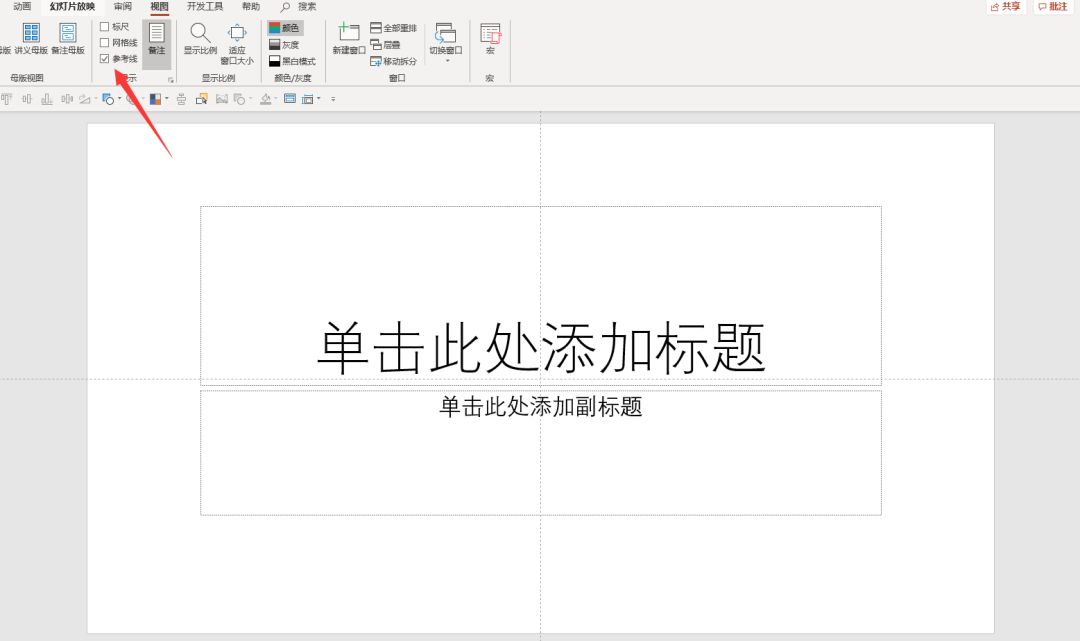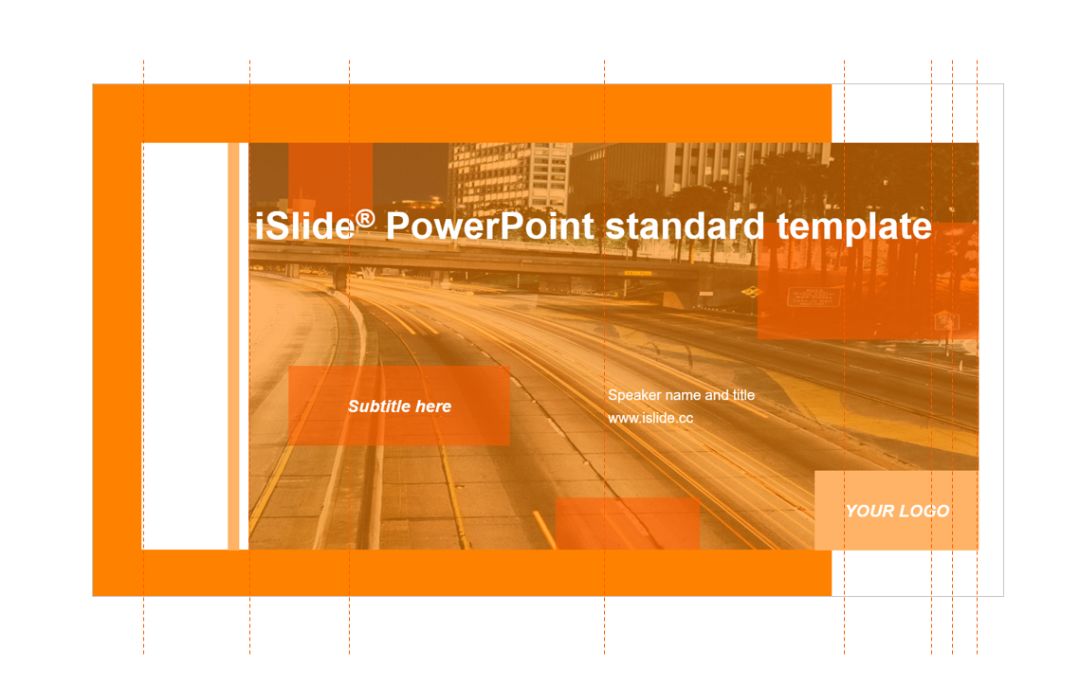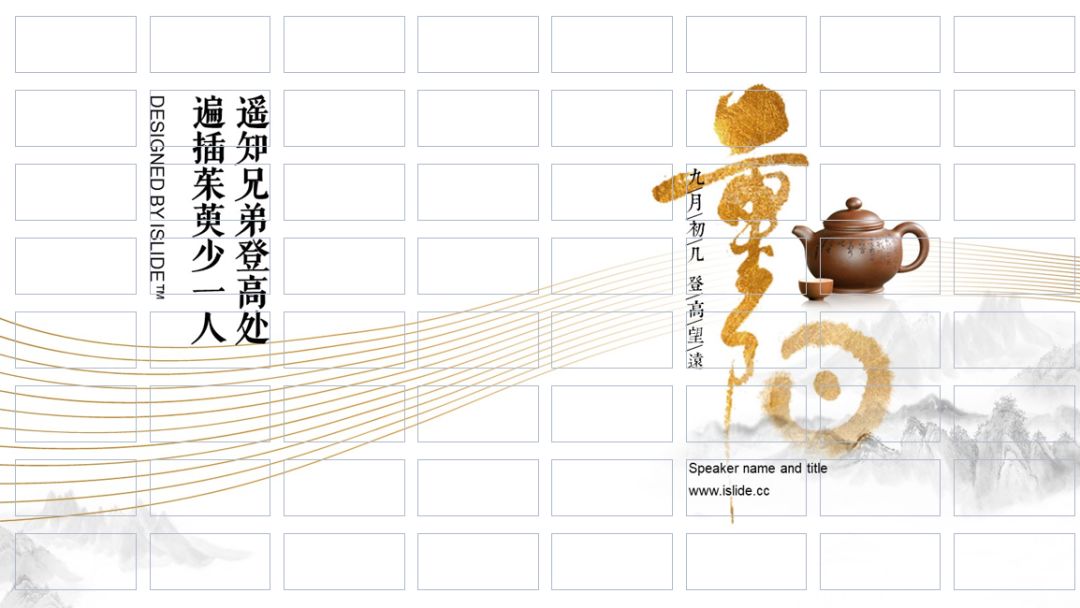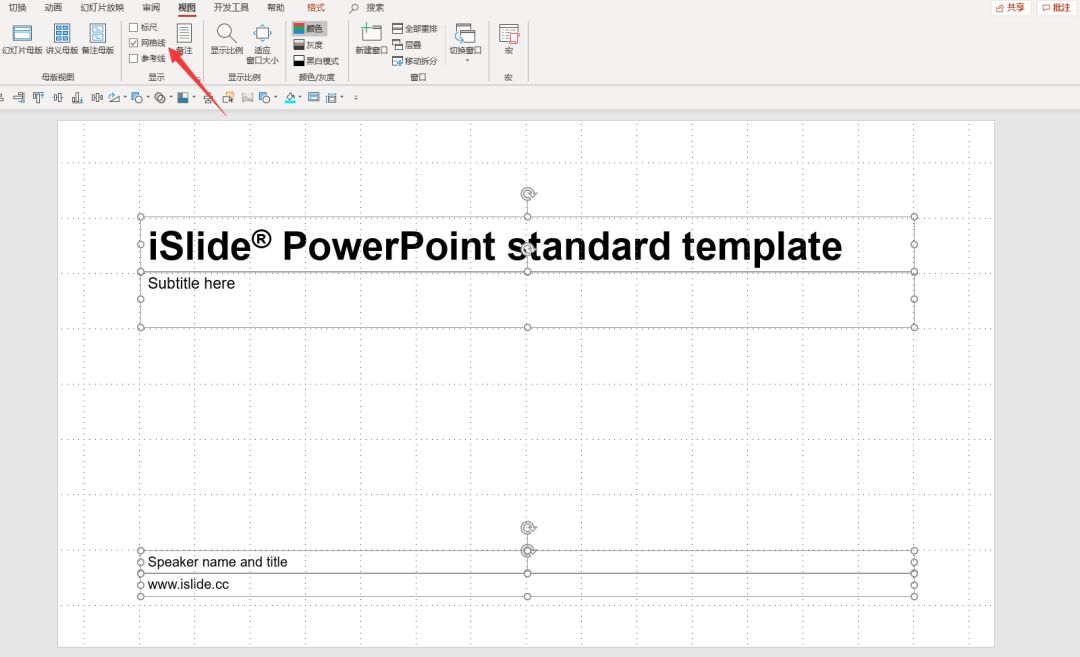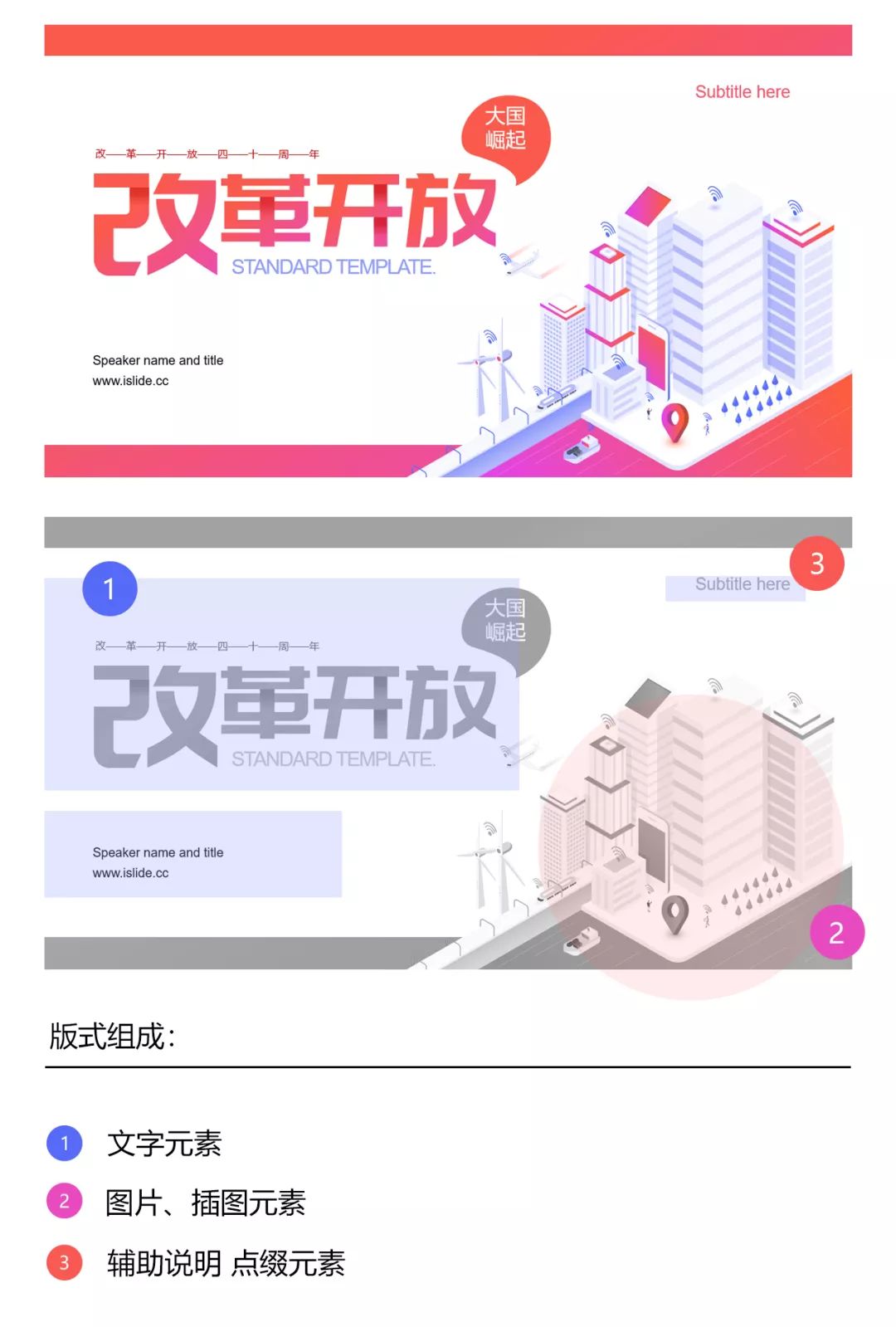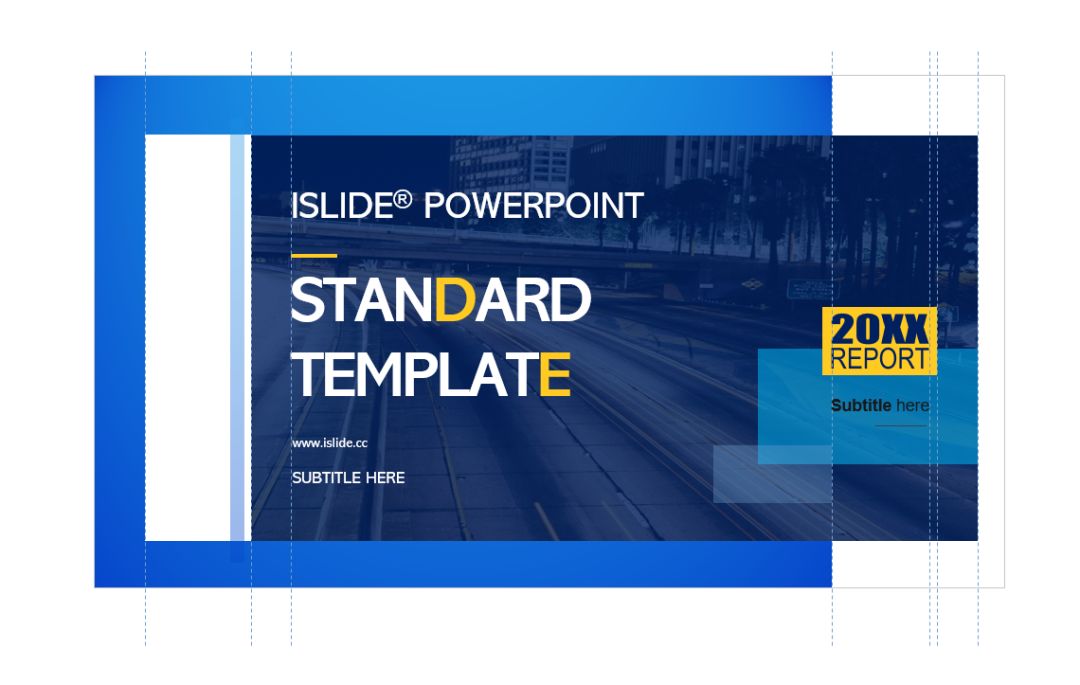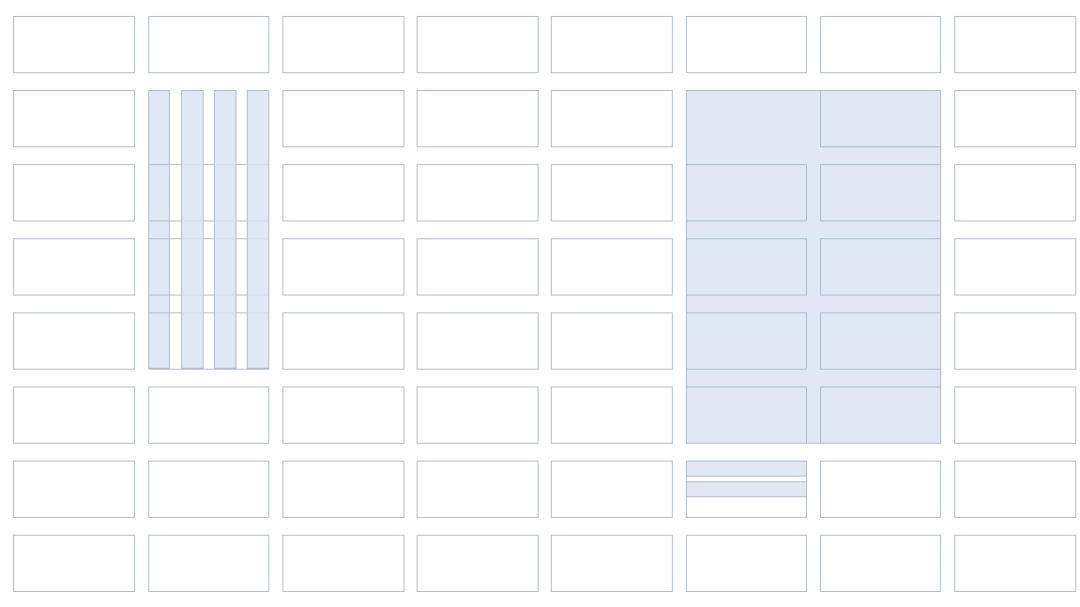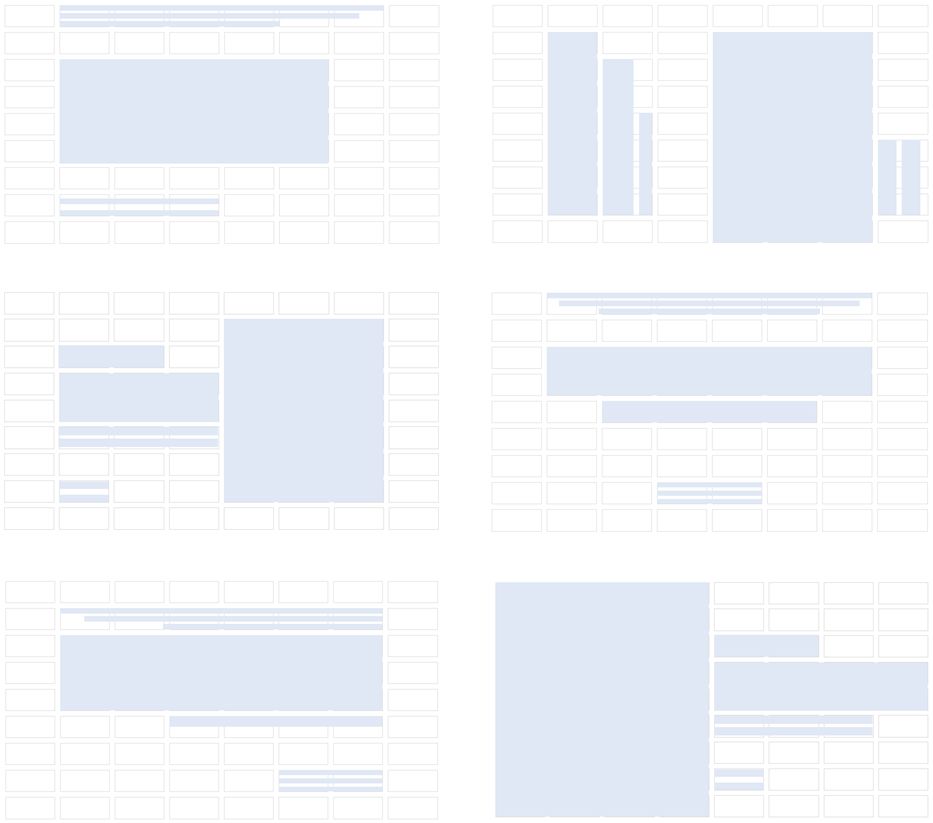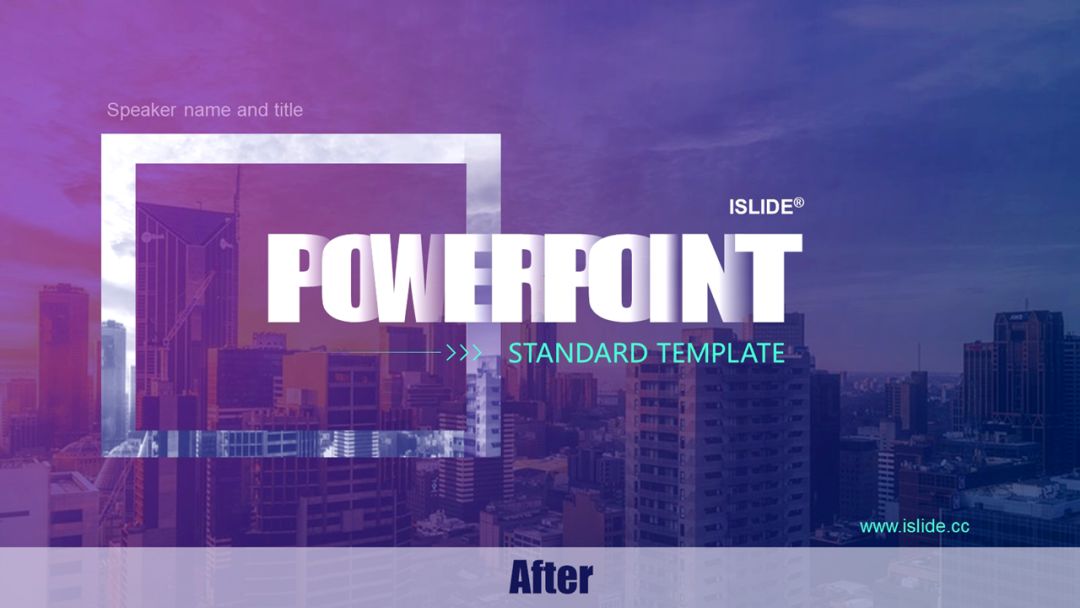
如何优化PPT的版式,做好PPT版式的技巧
说到PPT版式,很多同学都没有很深的研究,
其实把版式做好了,PPT的颜值可以有很大提升。
我们先来了解下一页PPT的版式构成三元素:
根据下图可知,我们常见的版式3元素包含:文字、图片和辅助元素。
从很多教程以及PPT文章里都讲过图片在PPT里的应用和排版,但是在PPT设计(尤其是PPT封面)中,文字元素的设计是一大核心点,但同时又特别容易被我们忽略。
所以今天这篇教程就分享了一些文字的排版技巧,希望对大家有所帮助。
01
[文字元素的对齐]
首先,来看一个例子,拉一些辅助线可以看到 这个画面中几乎没有元素是对齐的,所以PPT看起来会非常凌乱。
接下来我们把文字元素做一些调整,进行对齐后,整个画面看起来就会清爽干净很多。
所以在没有很强的版面掌控力之前一定要慎用一些倾斜、跳跃的排版方式,处理的不好反而会适得其反。
那么如何在PPT中实现对齐呢?
方法1.借助辅助线
在PPT视图菜单中勾选参考线,屏幕中会出现十字虚线。
也可以用快捷键alt+f9快速调出或隐藏。
拖动虚线辅助文字元素对齐:
复制辅助线:按住shift拖动
删除辅助线:拖动到PPT页面外
方法2.借助网格系统
早在20世纪初,德国、荷兰、瑞士等国的平面设计师们就开始提倡用客观的设计原理进行文字的编排,二战后这种理念在瑞士得到了良好的发展,直到20世纪40年代后期,第一次出现了使用网格进行辅助设计的印刷作品。由瑞士设计大师约瑟夫·米勒-布罗克曼所著的《平面设计中的网格系统》一书,自1961年出版以来畅销至今,对设计界有着深远的影响。目前,网格系统已经广泛地运用在杂志、平面设计、网页设计、移动端界面设计之中。
在PPT的视图菜单中点击网格,屏幕中便会出现网格线。
同时我们也可以根据PPT的内容 、图文疏密等方面去设计一套网格。
通常格子越多,版面的灵活性就越大。
在网络系统内有非常多的可能性去灵活安排版面内容:
网格也不一定非得是等分的,如何设计取决于设计内容的特点和图文的比例。
(留白部分也是版面中的元素哦)
当然,我们也不用每次都很复杂的设定一个网格系统来进行元素对齐,但是我们可以了解学习他的原理来帮助我们对版面进行排列。
02
[改变文字的层级关系]
改变文字的层级关系,换句话说就是在文字上做出对比。
缺乏对比,画面会变得平淡乏味并且不能有效的传递信息,运用好对比,可以在有限的空间里明确重点,让观众更舒适的阅读信息。
那么我们可以通过哪些方面来改变文字的层级关系呢?
1、文字的大小
拉大不同层级间的字号差距,能使阅读和视觉的定位更加明确。
2.文字的粗细
通过不同粗细的文字配合,可以增加整体的视觉节奏感
3.文字的色彩
在色彩的明暗、冷暖上做对比。
同时,我们还要根据信息的重要性对元素进行组合和配比,决定哪个占的比例更大,哪部分更应该突显。
接下来我们运用这个思路来对案例进行调整,
下图虽然是做了一些层级对比,但是层级平均,没有鲜明的对比效果,所以画面就会显得层次感不够。
在调整时放大加粗了主标题,缩小了次要文字作为装饰和说明,使文字排版上有了轻重分明的节奏表现。
所以在文字上做对比时,对比效果一定要明显,这样才能制造出视觉焦点。
03
[文字和画面的搭配]
1.文字和画面搭配是否平衡
画面中,左重右轻,右重左轻,头重脚轻,元素过于分散等等都是不平衡的:
重要的是重心与位置,要让画面更像是一个整体,而不是零碎的个体。
2.文字在画面上的可读性
这张PPT,当蓝色文字被安排在蓝色背景上时,由于和图片的颜色太过接近,文字识别性就会变得较差。
通过改变背景和文字颜色来保证文字的识别性:
04
[文字版式番外]
多看多临摹多练习
其实PPT封面和banner、网页、画册的布局比例都很相似,所以我们可以从优秀网站和杂志作品中去学习提升。